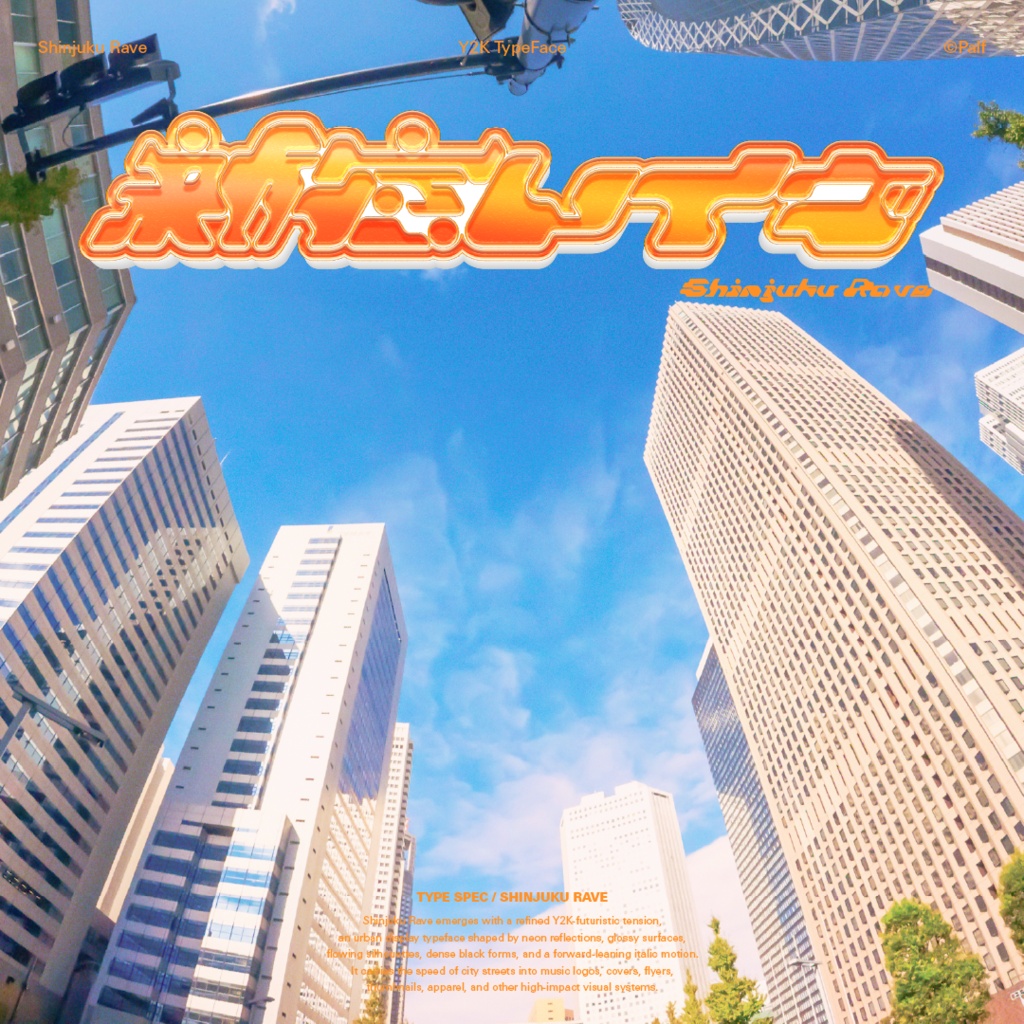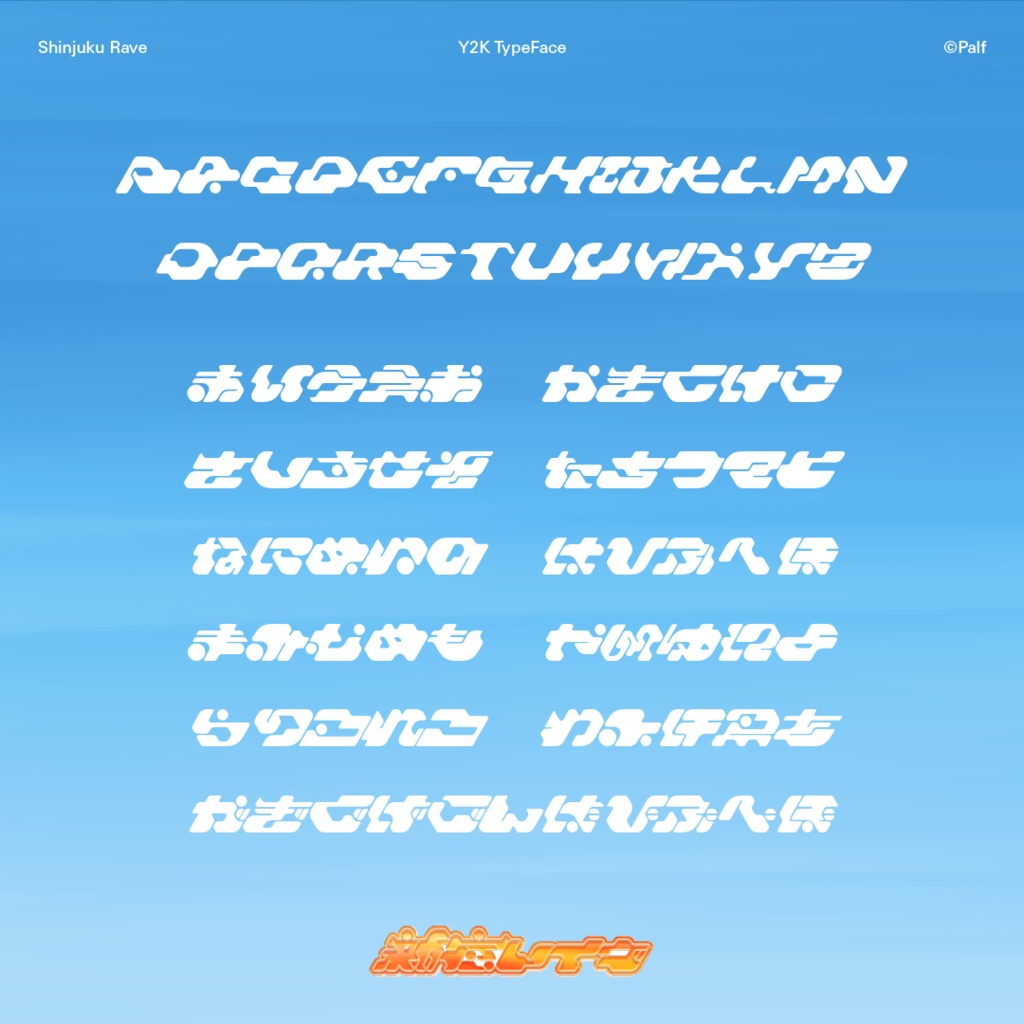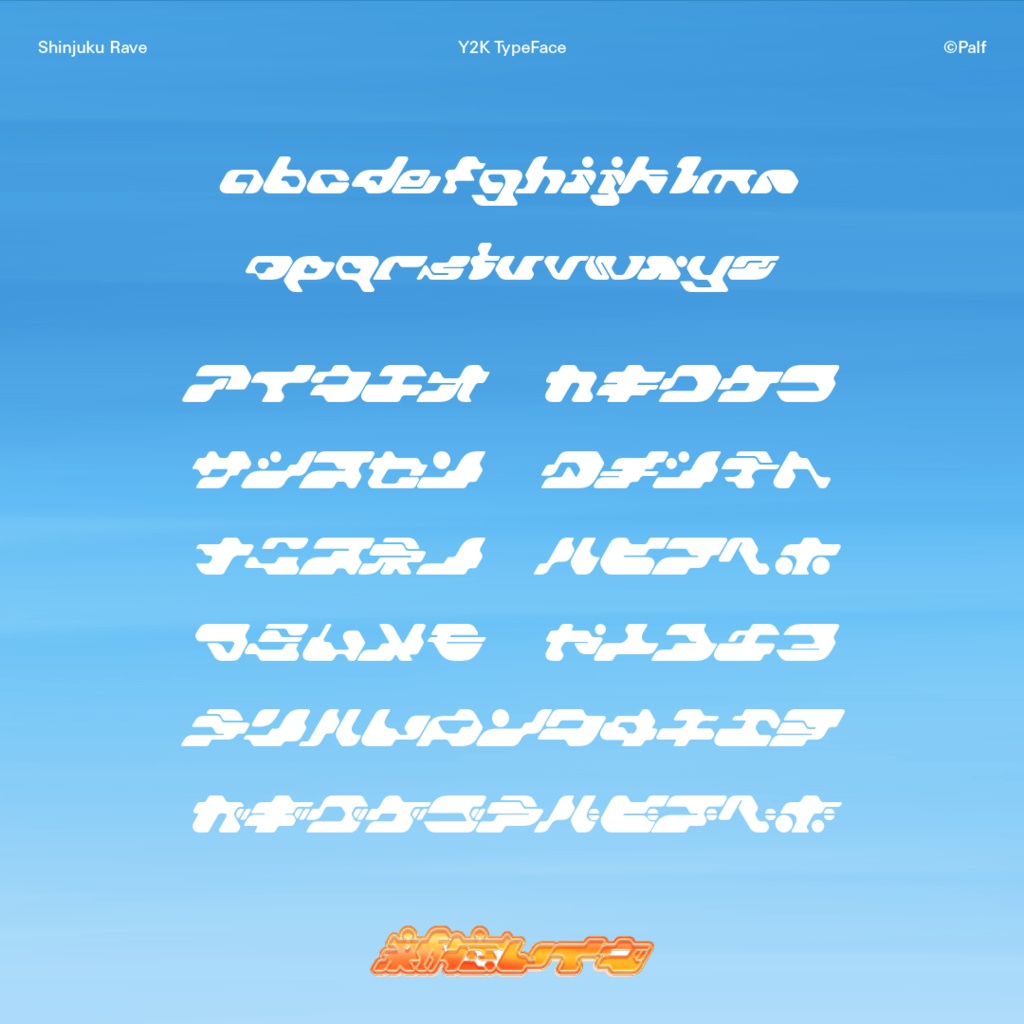
新宿レイヴ【フォント】
Y2K・都会感・未来感をテーマにしたディスプレイフォントです。 強い斜体によって疾走感と存在感を演出します。 MV向きとして制作しています。 今後歌詞ハンドルネーム頻出漢字に基づいたMV用漢字セットを収録する予定です。 【フォント仕様】 ひらがな・カタカナ・ラテン文字・漢字2文字(新宿) 277グリフ/276文字収録 OpenTypeフォント / TrueTypeフォント 【利用規約】 当フォントをご利用された時点で、この利用規約に同意したものと見做します。 当フォントデータは、本規約に定める条件でご利用者様に使用する権利を許諾します。 当フォントの著作権やその他一切の権利はPalfに帰属します。 ●使用条件 1) 2人以上の複数人でご利用になる場合のみ、1ライセンスにつき端末3台までといたします。 2) 本フォントを使用して得られる結果については、仕様者自身が責任を負うものとします。 3) 一般印刷物の作成(ポスター、書籍、フライヤー等)にご利用いただけます。 4) 立体制作物の作成(ステッカー、Tシャツ、アクリルキーホルダー等)にご利用いただけます。 5) 映像及びWebに関連する制作物に於いては、画像化・アウトライン化した上でご利用いただけます。 6) ロゴマーク、タイトルデザインの作成にご利用いただけます。 7) 画像化・アウトライン化したものを加工・変形してご利用いただけます。 8) 購入者本人又は事務所内等での限定した使用に限り、当フォントファイルを改変し、本人のみが使用することができます。 ●禁止事項 当フォントファイルを使用する際、以下の事項を禁じます。 1) 第三者への譲渡・貸与・配布・販売 2) 当フォントデータを元とした、類似又は同一フォントのデータの作成 3) 公序良俗に反する目的、誹謗中傷目的での使用 4) 政治的・宗教的利用 5) 犯罪への利用 6) 当フォントのサーバー上へのアップロード 7) 当フォントデータを取り出すことができるソフトウェアへの組み込み ●その他 ・上記に記載されていない事項については、著作権法及び関連法規に従うものとします。 ・本利用規約は予告なしに変更されることがあります。